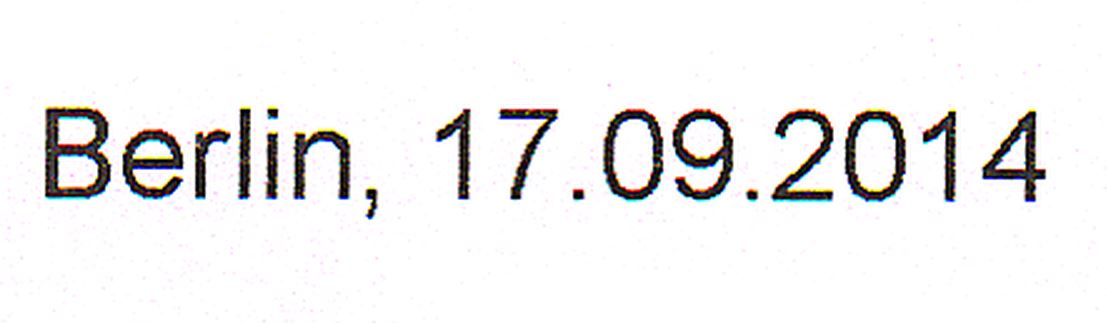
Suche tatsächlich nur diese einfache Schrift
Da ich keine Ahnung von Schriften habe und auch nicht weiß, wie ich mir selbst eine Schrift erschlißen kann bzw. wo ich danach suchen könnte frage ich hier.
Kann mir jemand sagen, wie diese Schrift heißt?
Sind diese "bunten Pixel" eine Besonderheit, die zur Schrift gehören oder ist das einfach schlechte Qualität?
Das dürfte mit hoher Wahrscheinlichkeit die Schriftart Arial sein.
Die Abbildung wirkt wie ein Ausdruck eines Screenshots, was auch die »bunten Pixel« andeuten. Also eine reine Besonderheit der Bildschirmdarstellung. Das hat mit der Schrift selber nichts zu tun.
Das sieht für mich aus wie ein Scan eines Ausdrucks. Beim Scannen auf Büroscannern kommt es gern mal zu solchen Farbverschiebungen.
Ob das die Arial ist, bin ich mir nicht sicher – das Komma und der quadratische i-Punkt sprechen eigentlich dagegen. Vielleicht gib’s aber auch irgendeine Arial, die diese Merkmale hat.
Ja, kann auch sein. Aber sieht das Ergebnis dann sooo pixelig aus?
Ist mir auch aufgefallen, aber das hätte ich jetzt auf das Hinting bzw. die Reproduktion geschoben.  :-?
Ich tippe auf einen kleinen Schriftgrad und einen sw-Laserdrucker. Am 4er siehst du schön die Treppen …
Das ist doch eher irgendein Thermodrucker (Parkscheinautomat, Registrierkasse o. ä.), und die sehr spezielle Kombination der Frage nach dieser Schrift (wer sucht denn bitte die Langeweile in Schriftform) den Farbpixeln und dem Inhalt des Musters riecht mir ja ein bißchen so, als will da jemand ein Dokument nachträglich … ähm … »verändern«. Hab ich recht oder hab ich recht, Fontiger?
Tatsächlich möchte ich es aber nicht verändern sondern wiederherstellen.
Ja, mit den Jahren entwickelt man einen Blick dafür. ;-)  Wenn Du uns gleich verraten hättest, daß das ein Print aus so einem Automaten ist, hätten wir Dir auch gleich sagen können, daß diese Geräte oft interne Pixelschriften haben, die weder technisch noch optisch genaue Entsprechungen bei Rechnerschriften haben.